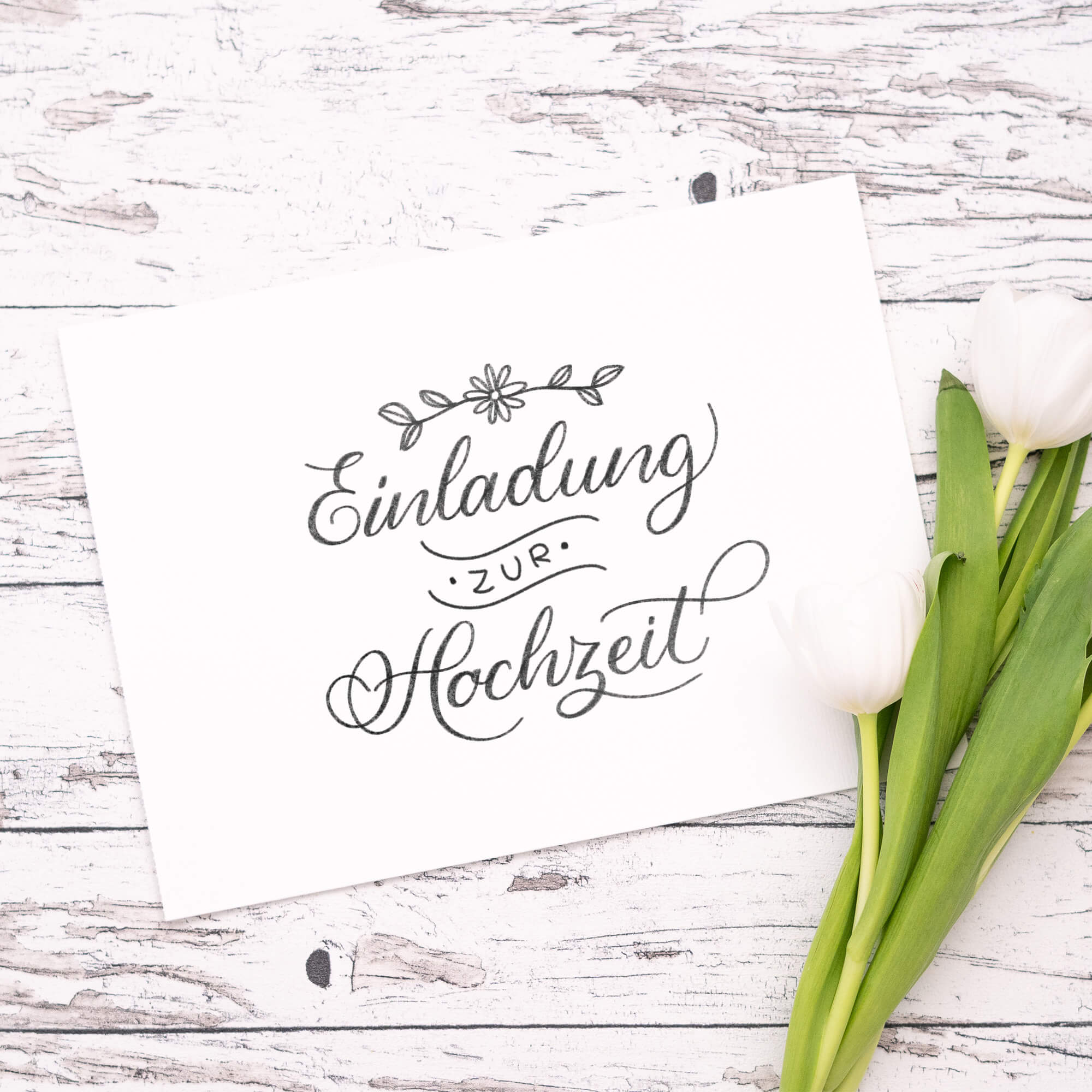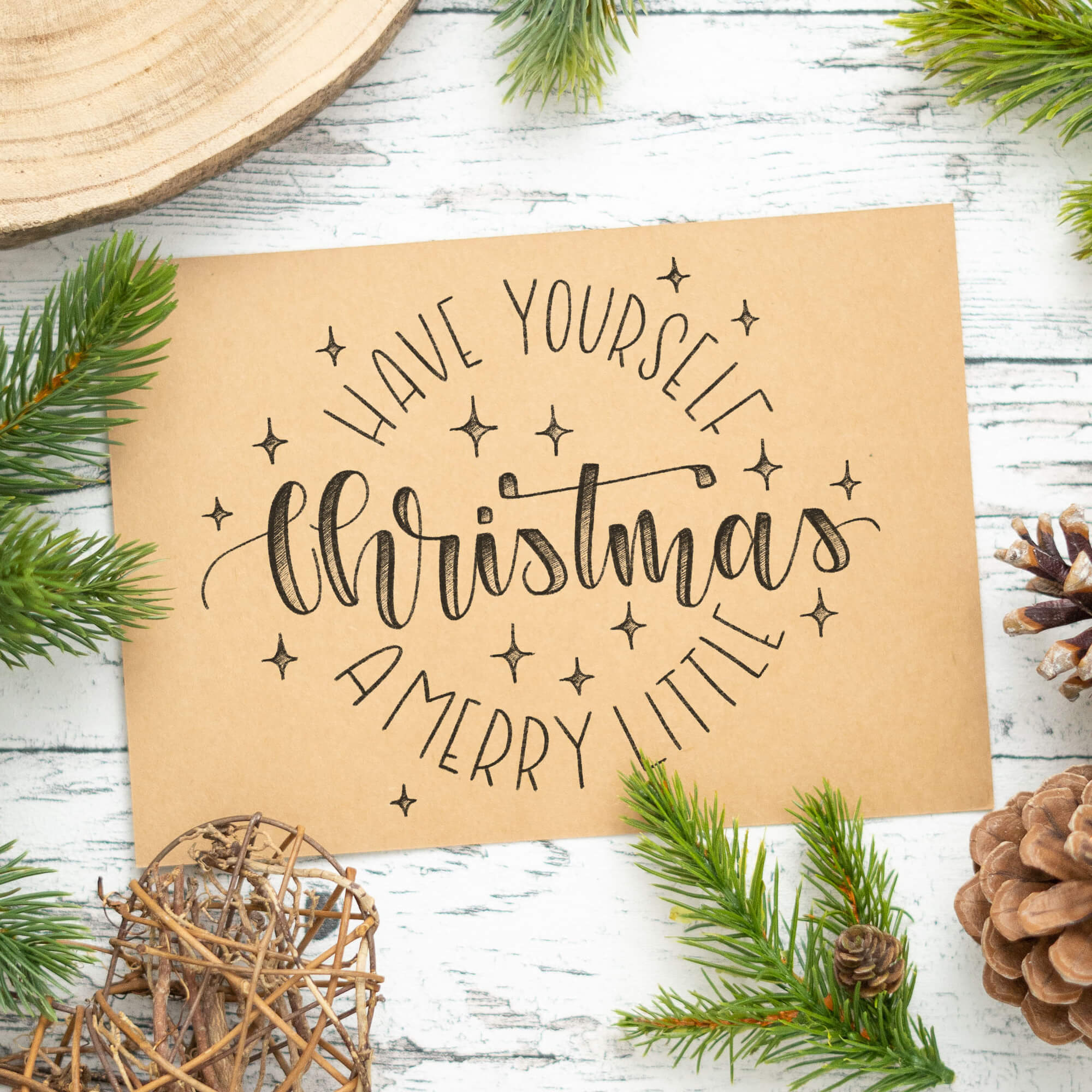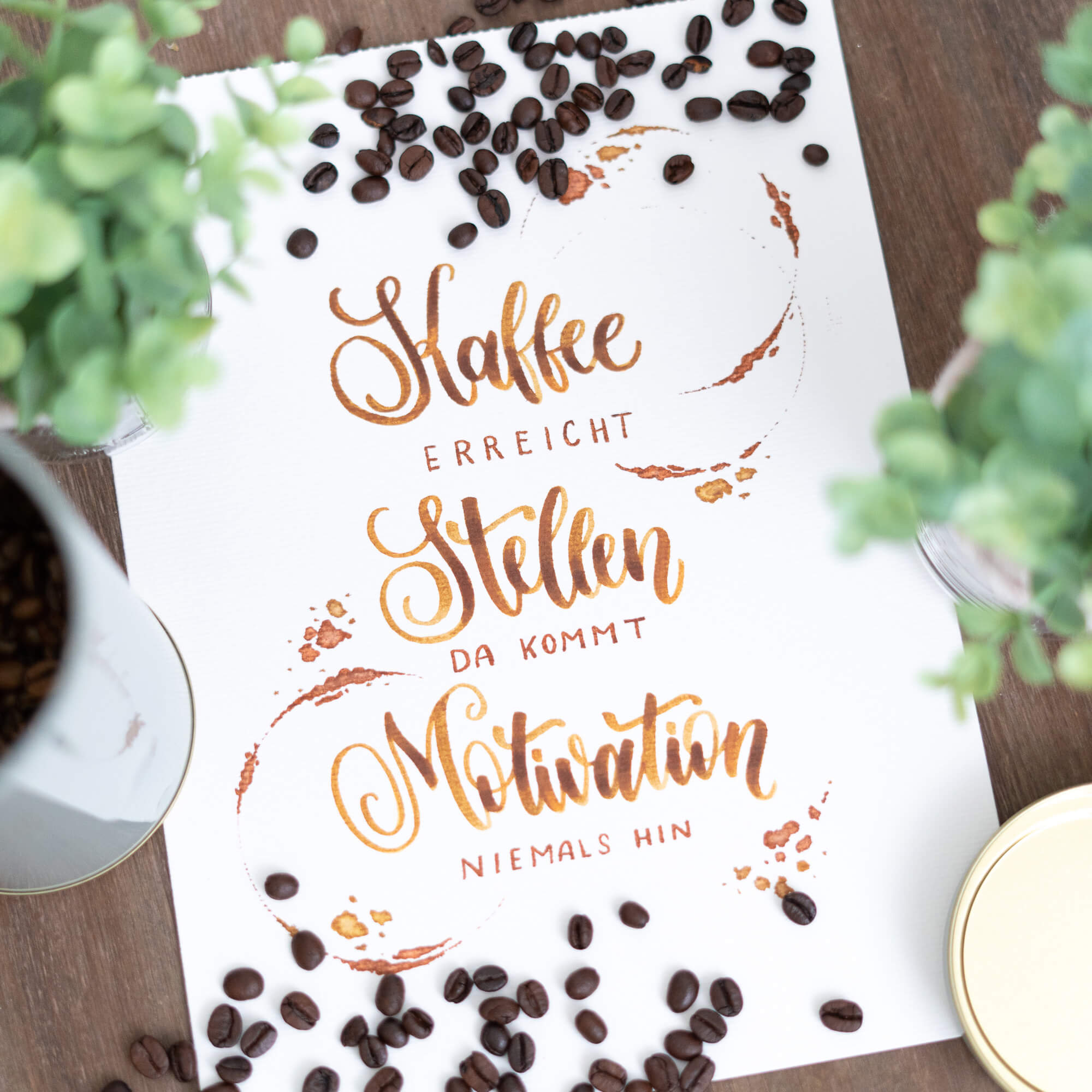
Charmante Handlettering-Kompositionen für alle Anlässe!
Entdecke wunderschöne Ideen für Geburtstage, Hochzeiten, Einladungen und vieles mehr. Komplett handgezeichnet.
Perfekt als Inspiration oder Vorlage zum Ausdrucken.
Vorlagen für alle Fälle
Egal wie kreativ man ist – manchmal fehlt einfach der erste Impuls oder die zündende Idee.
Ich verspreche dir: Ein Blick auf die vielen unterschiedlichen Kompositionen ist nicht nur motivierend, sondern lässt die eigenen Ideen (wieder) sprudeln!
Dein treuer Begleiter
Natürlich kannst du die Vorlagen auch direkt abpausen und in deinen Projekten nutzen.
Was du bekommst
- PDF mit 100 Handlettering-Kompositionen in ganz unterschiedlichen Stilen. Verschiedene Schriften, Dekorationen und Symbole harmonisch kombiniert.
- 10 Seiten mit Sammlungen zu Themen wie Dankbarkeit, Geburtstage, Wünsche, Einladungen, Willkommensgrüße, Natur, Herbst, Winter und Weihnachten.
- Jede Komposition ist ein eigenes kleines Kunstwerk und lässt sich 1:1 nutzen oder mit anderen Layouts kombinieren
Die Sammlung dient vor allem als Vorlage und Inspiration. Sobald du siehst, was alles möglich ist, kannst du die Ideen auf deine eigenen Kompositionen übertragen.
Alternativ kannst du die Kompositionen nachzeichnen oder direkt verwenden.
Die bist völlig flexibel in der Materialwahl. Alle Ideen lassen sich entweder ganz einfach mit Papier und Bleistift umsetzen oder mit Hilfe von Brushpens, Markern, Gelrollern und weiteren typischen Stiften verfeinern.
Kompositionen bestehen immer aus mehreren Elementen, die in Einklang gebracht werden. Im Falle des Handletterings geht es darum, verschiedene Schriften und Symbole so zu kombinieren, dass ein harmonisches Gesamt-Kunstwerk entsteht.